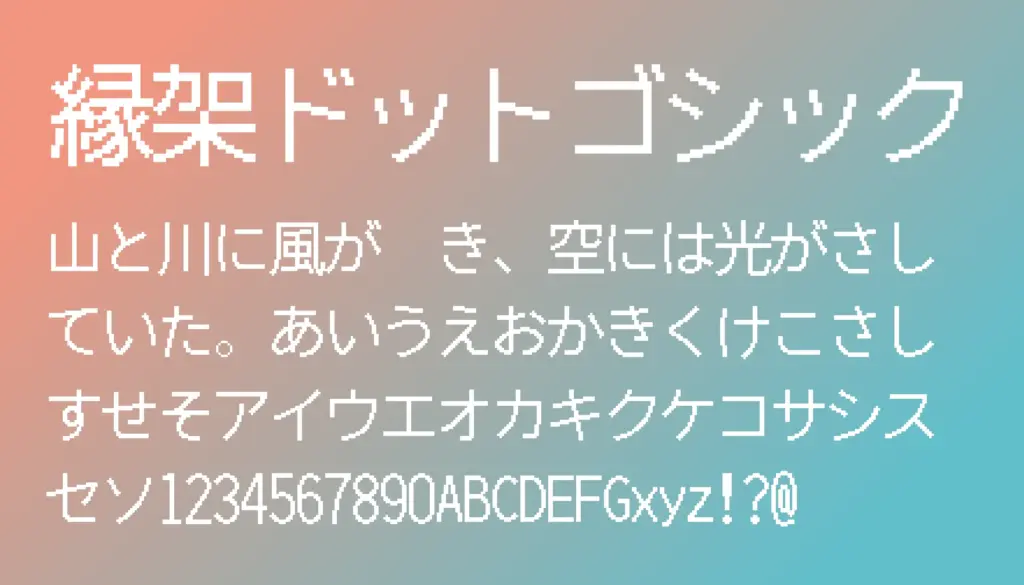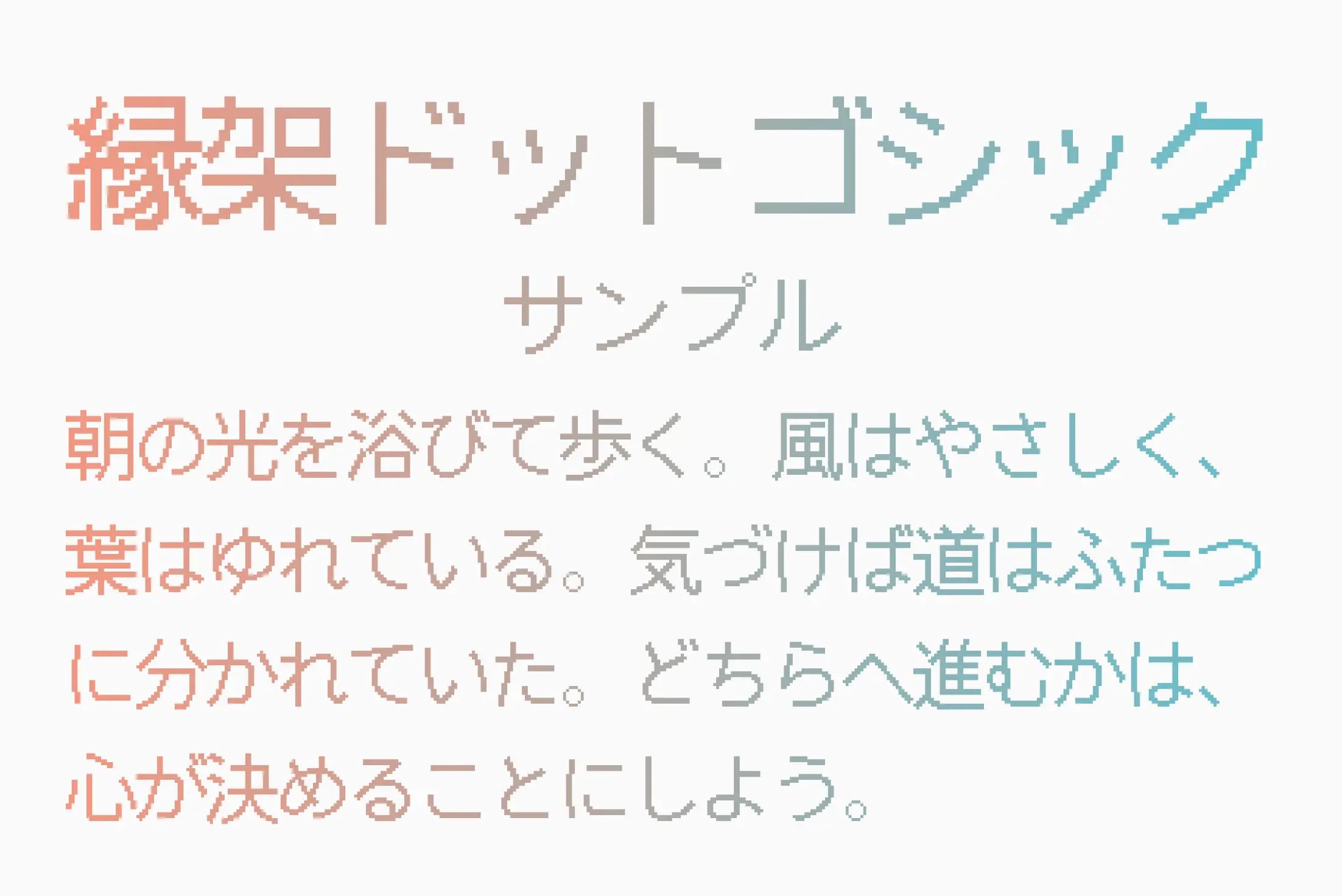
文字サイズ24ドットをベースにデザインされており、栄養表示、領収書、鉄道標記、商品ラベル、レシート印刷などに限りなく近い“見覚えのある”文字を実現します。パキッとした視認性と等幅気味のバランスが取れており、レトロ感と実用性が共存。ZINEやパロディ、シュール系デザインにも最適です。
縁架ドットゴシック